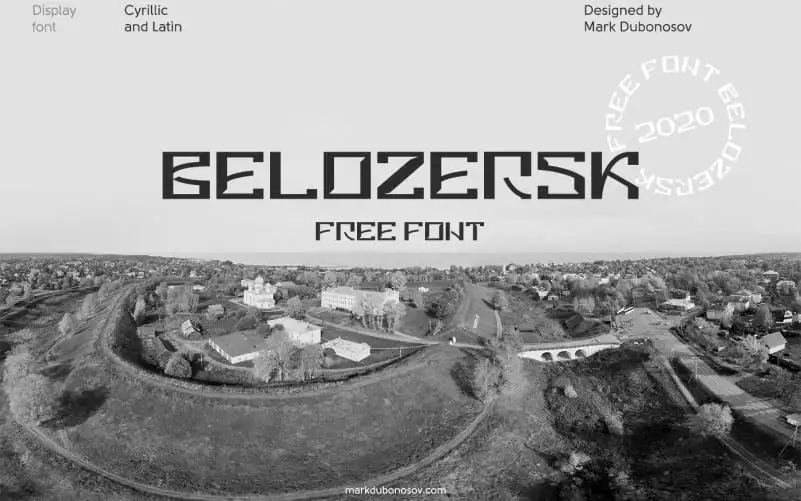
Belozersk Display Font – Fonte Grátis
Belozersk Display Font
Belozersk Display Font é uma fonte de exibição inspirada na arte vitoriosa que transmite um visual autêntico e cuidadosamente elaborado. Ela foi criada por Mark Dubonosov e traz letras simples, clássicas e elegantes. Esta fonte é perfeita para uso em grandes projetos, títulos, headlines de sites e textos curtos. Belozersk está particularmente bem adaptada para marcações, logotipos, anúncios, títulos e design editorial. É uma fonte livre tanto para uso pessoal quanto comercial — não há necessidade de créditos ou licenças adicionais. Com sua simplicidade elegante e inspiração vintage, Belozersk traz um toque único ao seu projeto.